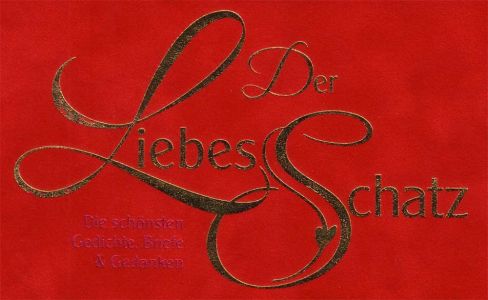
Suche Namen dieser geschwungene Schriftart
Wer kann mir sagen wie diese Schrift heißt in der das D, das S und das L geschrieben sind?
Da die Frage beantwortet ist, nutze ich die Gelegenheit für eine Offtopic-Frage:
Wie kommt es eigentlich dass man solche Schriften aus dem Stehgreif kennt? Das sind ja jetzt nicht die gängigen Sachen. Zufall? Schriftarchiv im Kopf? Sehr gute Suchmethode?
naja, Übung sage ich mal. Bei solchen verspielten kalligraphischen Werken ist der erste Weg zu Rob Leuschke oder Ronna Penner. Bei klassicheren kalligraphischen Schriften würde ich die (Charles) Bluemlein Scripts von Alejandro Paul (Sudtipos) als erstes durchsuchen. Und, naja, die Love Light kommt so ein bis zwei mal die Woche auf WTF daher … ;-)
In diesem speziellen Fall hab ich aber ganz profan das Stichwort "heart" (wegen der Herzchen im Font) auf WTF eingegeben … :D